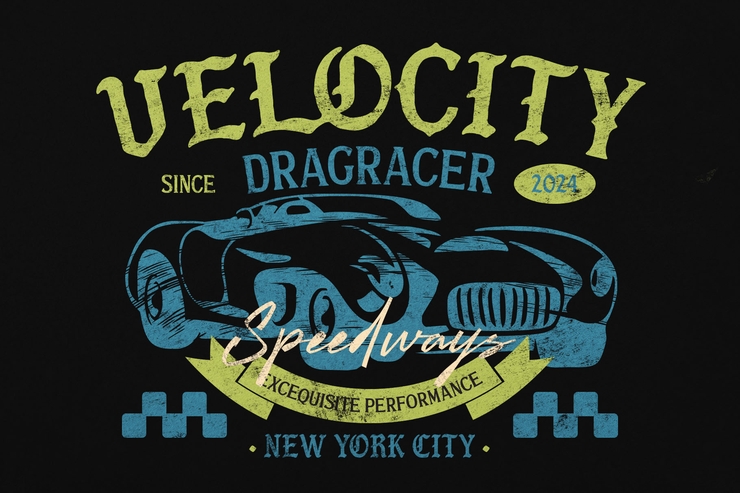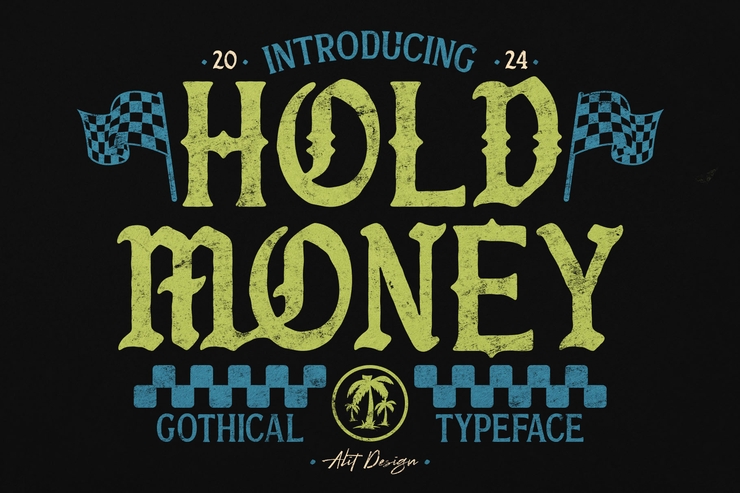
Hold Money Modern Bold Finance - Stil dekorative englische Schrift
Hold Money ist eine auffällige dekorative englische Schriftart zum Thema Finanzen, die mit kräftigen, stabilen Strichen und soliden geometrischen Strukturen gestaltet ist. Sie vermittelt Reichtum, Vertrauen und geschäftliche Vitalität und passt perfekt zu Finanzprojekten, Investmentmarken und kommerziellen Marketingvisualitäten. Diese stilvolle Schrift wird häufig für Finanzlogos, Bankplakate, Geschäftsbanner, währungsbezogene Verpackungen, Finanzinhalte in sozialen Medien und wirtschaftliches Grafikdesign verwendet. Komplett mit Groß- und Kleinbuchstaben ist sie hochgradig skalierbar und lässt sich leicht an Farben, Größen und Layouts anpassen, wobei die stabile Premium-Textur erhalten bleibt. Geeignet für Grafikdesigner, Finanzinstitute und kommerzielle Markenprojekte, um auffällige visuelle works.Free für den kommerziellen Gebrauch zu schaffen / Kein Copyright